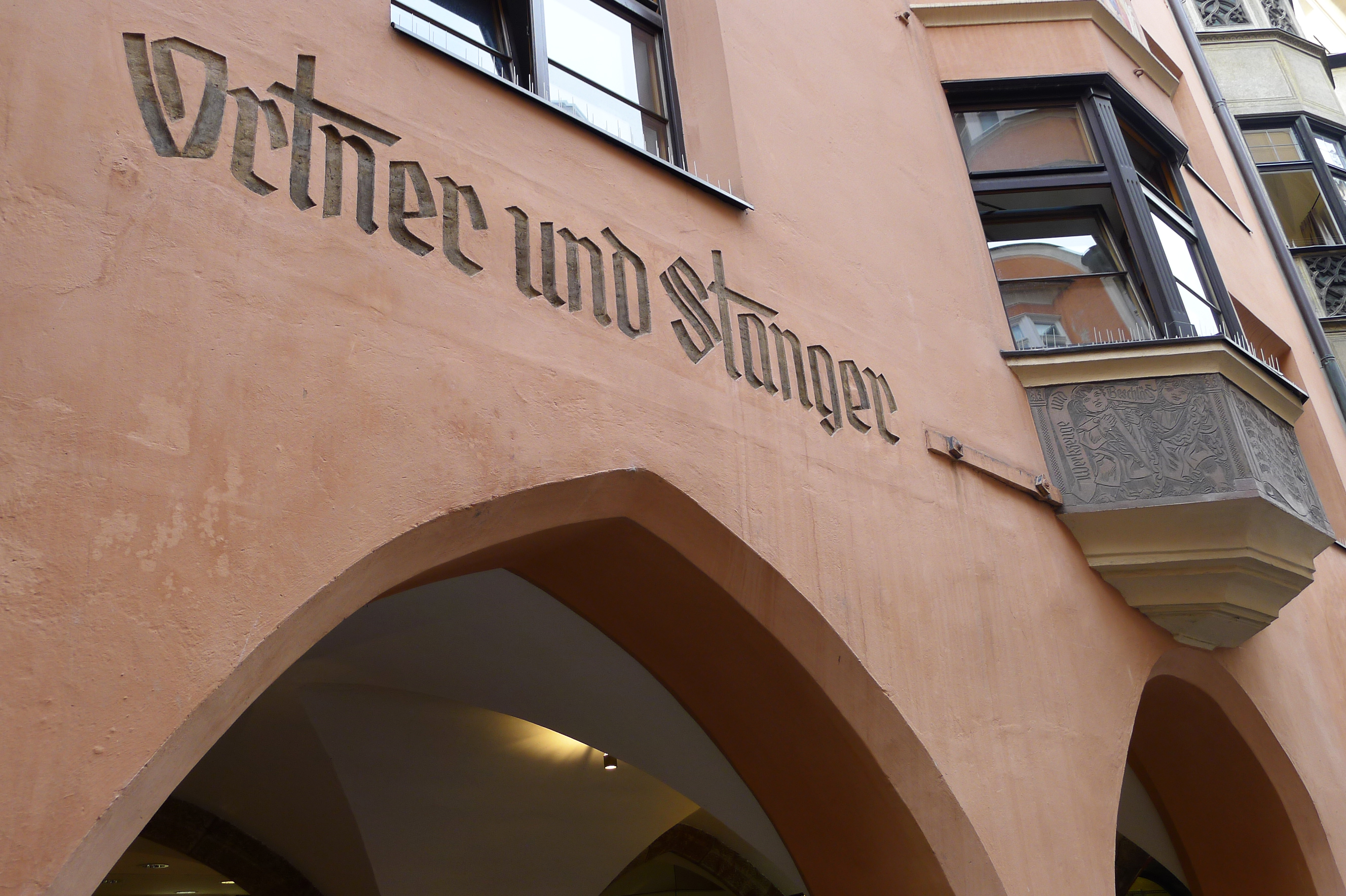
Ortner & Stanger
Das „Ortner & Stanger“ Logo am Geschäftslokal unter den Lauben der Innsbrucker Alstadt wurde vom wohl bekanntesten Tiroler Grafiker Arthur Zelger entworfen, obwohl man das nicht auf Anhieb vermuten möchte. Er hat durch die Wahl der Fraktur das typische Ambiente und die Geschichte der Altstadt aus der Zeit Maximilians I. einfließen lassen. Durch ein paar grafische Tricks ist sie dennoch als "jetzig" erkennbar.
Sie wird bis heute vom Unternehmen verwendet. Unter Kaiser Maximilian I. wurde übrigens die erste qualitätvolle Fraktur geschaffen – für sein Werk "Theuerdank", in dem er seiner angebeteten Maria von Burgund seine Heldentaten schildert. Sein Goldenes Dachl steht in Sichtweite, an der Präsenz des Paares am Prunkerker ist zu sehen, dass sein früher "PR-Gag" von Erfolg gekrönt war.
Innsbruck, Altstadt